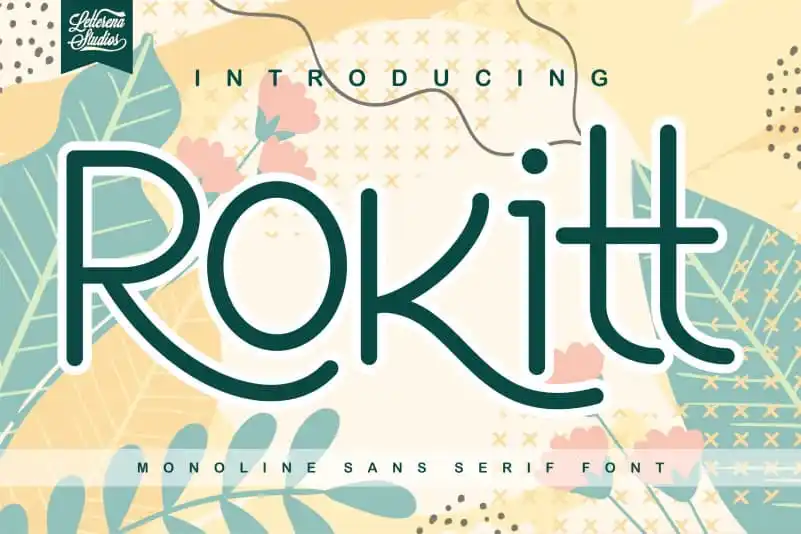
Rokitt – Monoline Sans Serif Font – Download Grátis
Esta fonte é perfeita para projetos de design que valorizam uma sensação natural e minimalista. Com seu design monolinéico, Rokitt – Monoline Sans Serif Font oferece um equilíbrio elegante entre estética e legibilidade, ideal para textos em páginas web ou materiais de marketing. Inspirada na simplicidade da natureza, essa fonte transmite uma sensação fresca e moderna que se assemelha a linhas de árvores ao vento ou à forma geométrica das folhas num dia ensolarado. Com seu designer leteranastudios, Rokitt – Monoline Sans Serif Font proporciona um toque distintivo aos projetos digitais, oferecendo uma opção versátil que se destaca em qualquer ambiente visual. Suas linhas retas e uniformes ajudam a criar uma identidade visual clara e profissional, ideal para aplicar em logotipos, banners de mídia social ou sites web. Além disso, o aviso de uso pessoal (apenas para uso não comercial) é um detalhe que ressalta a responsabilidade ética do designer ao oferecer recursos para designers que buscam combinar criatividade com lealdade e transparência. Com Rokitt – Monoline Sans Serif Font na sua ferramenta de design, você terá à disposição uma fonte única capaz de dar vida à sua visão gráfica, enquanto mantém a essência do uso profissional e ético para seu trabalho.